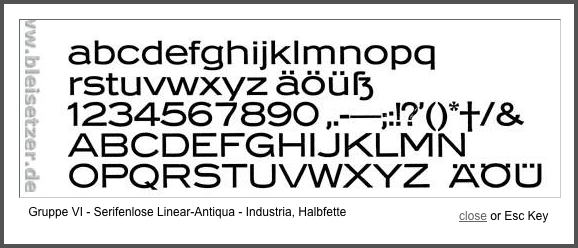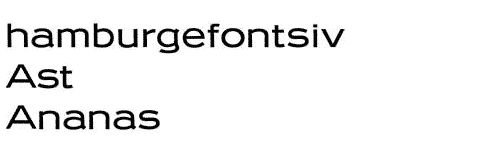
»Industria« digitalisiert?
Ich hoffe, das gehört wirklich hier hin:
Habe beim Herrn Bleisetzer diese tolle Grotesk gefunden (siehe Bild), dort heißt sie »Industria«. In der digitalen Welt findet man unter diesem Namen eine ganz andere Schrift.
Weiß jemand, ob's die hier schon in digitaler Form gibt? Sie gefällt mir ungemein (besonders a, g und ß!).
Oh ja, die istr schön. :D Dürfen wir darauf hoffen, dass Du uns die digitale Version erstellen willst , alls wider erwarten nicht doch eine bestehende auftaucht? Da ja Industria als Name wohl ausscheidet, wie wär es denn mit dem ursprünglichen Designer als Namensgeber? Zehnpfundt, das ist doch mal ein Name. :gimmifive:
Hab mich schon gefragt, ob ich mir die vornehmen soll, zum Üben ... Würd ich sehr gern! Aber das wird bestimmt ziemlich grottig im ersten Anlauf (und wird ne Weile dauern); tut mir irgendwie leid um die Schrift :shock:
Andererseits könnte man dann das lange z einbauen :P oh und wenn ich nur an die tz-Ligatur denke ... :biglove:
Wenn Ihr alle versprecht, mich heftig zu kritisieren, wenn ich mal nen Zwischenstand poste? – Aber vielleicht taucht sie ja auch noch auf.
Yeah, passt auch ja gut zu den Dimensionen der Guten :mrgreen:
Machen, üben, lernen :)
was kann schon verloren gehen außer hunderte Stunden "Arbeit"?
Dafür gibt's eine Schrift, Erfahrung, Erkenntnis und Zufriedenheit.
Vielleicht schon vor dem Start überlegen ob du eine 1:1-Digitalisierung machen möchtest, den Zeichensatz auf ein heute übliches Maß erweiterst, oder sogar manche Kleinigkeit bewusst änderst (z.B. ist das Ö wohl ein Bleisatz-Kompromiss, und warum das s so breit ist kann ich auch nicht ganz nachvollziehen).
Und das ß in Ehren, aber ist die Form im Detail nicht viel zu komplex im Vergleich zum Rest der Buchstaben? :|
Also die meisten Einwände von Sebastian kann ich zumindest nachvollziehen, aber das s ist super und soll gefälligst bleiben. :bandit:
Ja, und das find ich hier im Kontext genau richtig.
Machen! Und bloß nicht zu viel glätten! Die Schrift wird ja gerade interessant dadurch, daß sie an bestimmten Stellen Sehgewohnheiten ignoriert. Und eine weitere Helvetica extended braucht nun wirklich niemand. Gerade das ß sollte man schon 1 : 1 übernehmen.
Sebastian hat mit dem s schon recht, nimm mal Photoshop und setze das Wort "Ast". Die Versalumlaute riechen auch etwas muffig. Das ß ist ziemlich funky, sticht heraus, da die 3 nicht angepasst wurde, oder andersrum, das ß nicht "runder" gestaltet wurde.
Diese Schrift digitalisiert "mit einem Tröpfchen Gotham", dann fände ich das auch gut.
Ich hatte ja ein ähnliches Problem bei der Iwan (die da in den letzten Zügen liegt). Tschichold hat zwar Akzentzeichen gemacht, die sind aber für heutige Anwendungen derart ungewohnt dass ich mich dafür entschieden habe sie zu überarbeiten.
Die Frage ist wo man die Grenze zieht, zuviel modifizieren macht die Schrift auch kaputt.
Jetzt wo Poms mir beipflichtet mit dem "s" find ich es schon wieder schade wenn's verändert würde ... :?
Ich kenne eine ähnliche Schrift — allerdings eine extrem leichte — aus dem Buchdruck unter dem Namen »Koralle«. Habe aber leider kein Bildmaterial dazu.
ich find sie auch schön, gerade das sie ihre ecken und kanten hat, macht doch den reiz der schrift aus. ich schau mal später nach, ob ich ein schriftmuster davon habe ... schriftgießerei emil gursch, kommt mir irgendwie bekannt vor. laut global-type gibt es auch noch eine lichte (gravur) und ein paar andere schnitte. 28625.jpg wurde wohl auch von berthold vertrieben.
Ohh, das wäre klasse :biglove: Es gibt auf jeden Fall eines, das heißt »Industria, eine charaktervolle Reklame-Grotesk« – gefunden habe ich es nur in einer Unibibliothek in Harvard :oops: .. Eventuell kann ich da Bekannte zum Kopieren hinschicken, aber wenn Du eine vor Ort hättest, wär das natürlich einiges einfacher.
Die Schriftprobe gibt es übrigens einmal von 1913 direkt von der Schriftgießerei Emil Gursch und dann nochmal 1925 von Berthold, wobei sich die Formate der Publikationen leicht unterscheiden; das ist leider alles, was ich über die Suchmaske der entsprechenden Bibliothek (»industria grotesk« eingeben, reicht schon) finde.
habe paar schriftmuster gefunden und werde diese
kommende woche mal scannen.
Oh super! (Jetzt musste ich mir die Versalien aber verkneifen.) Tausend Dank. Freue mich drauf!
Ich hab schon ein bisschen grob angefangen. »hamburetoni« geht schon, wackelt aber alles noch ziemlich. Wird fein sein, eine etwas größere Vorlage zu haben :D